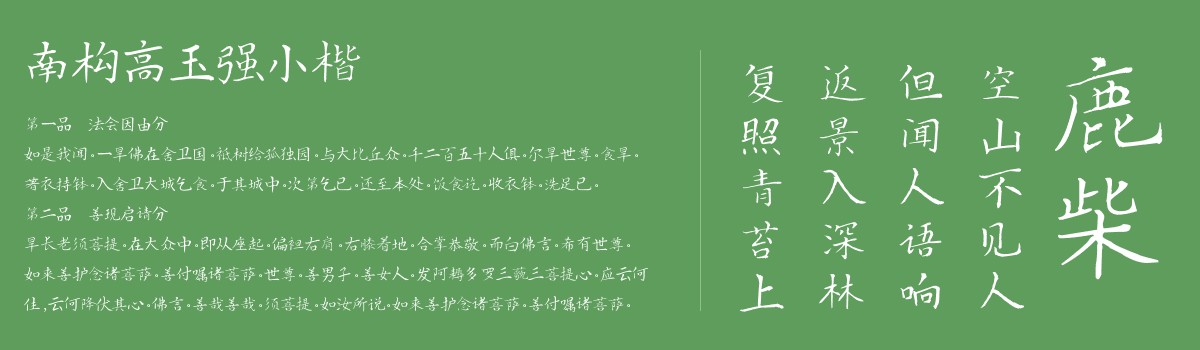
南构高玉强小楷
一款具有现代书风的小楷字体,字体结构严谨,刚柔并济,非常适合一些比较中国风的主题设计,用于副标题等都非常不错,这款字体是由字体家平台南构字库独家制作发行。
南构高玉强小楷
高玉强简介
高玉强,笔名:钱雨,河南安阳市人,自幼酷爱书法艺术,作品多次在比赛中获奖,多家报刊杂志发表,在临帖过程中临习颜真卿多宝塔,勤礼碑,欧阳询九成宫,王羲之兰亭集序,圣教序,
张迁碑,华晨碑,小楷主要是二王书体,洛神赋十三行,宣示表,乐毅论,自己还在不断的追求和完善个人书法风格。